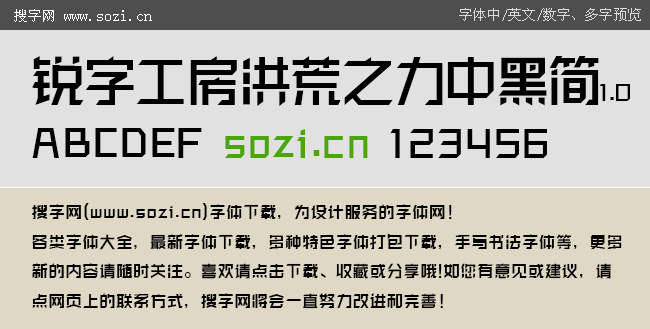
銳字工房洪荒之力中黑簡
搜字網(wǎng)提供一款非常藝術(shù)的黑體銳字工房洪荒之力中黑簡下載,銳字工房洪荒之力中黑簡是一款字形方正的銳字工房字體,該字體極具藝術(shù)感,簡潔大方,適用于包裝印刷、廣告設(shè)計(jì)、平面設(shè)計(jì)、書籍報(bào)紙等領(lǐng)域。